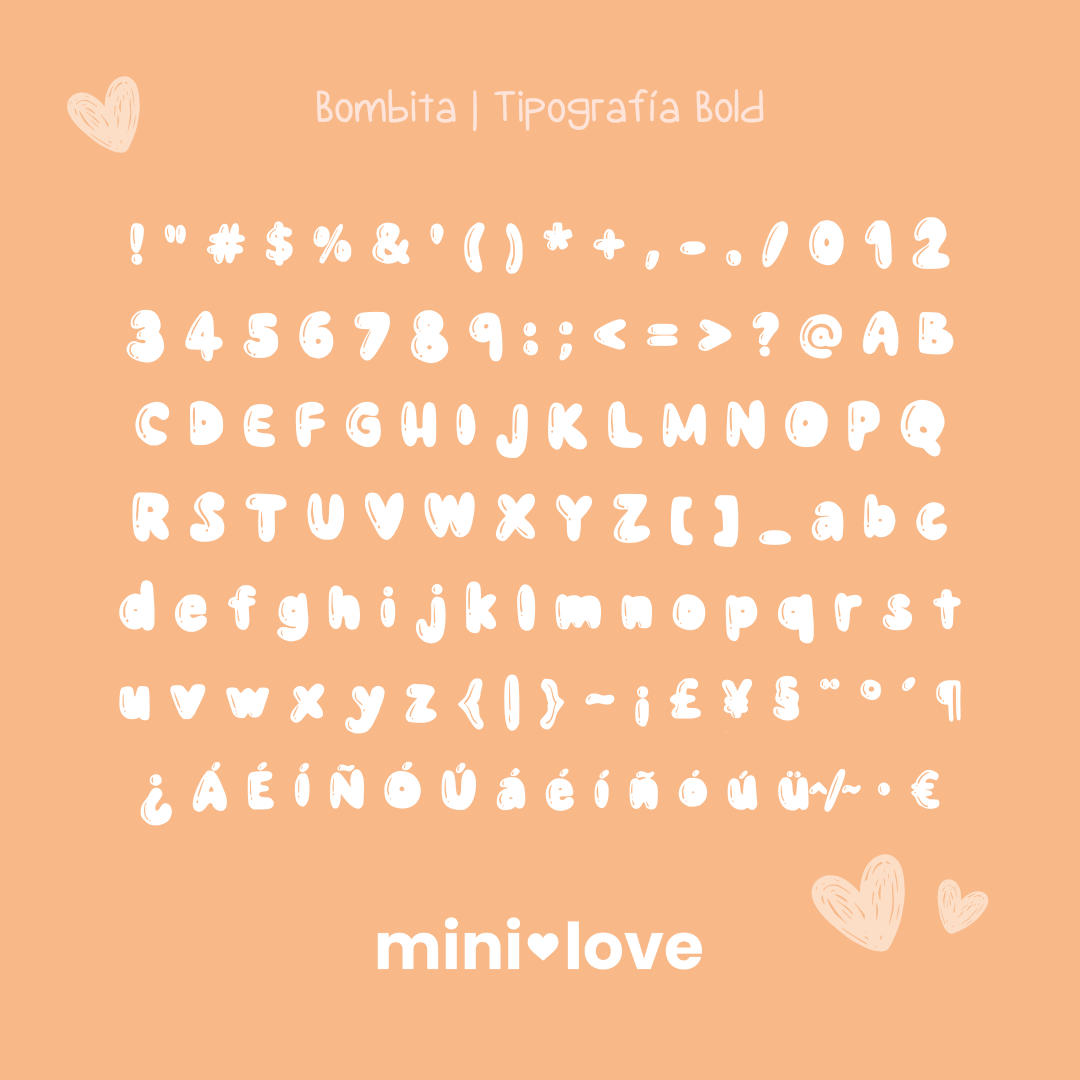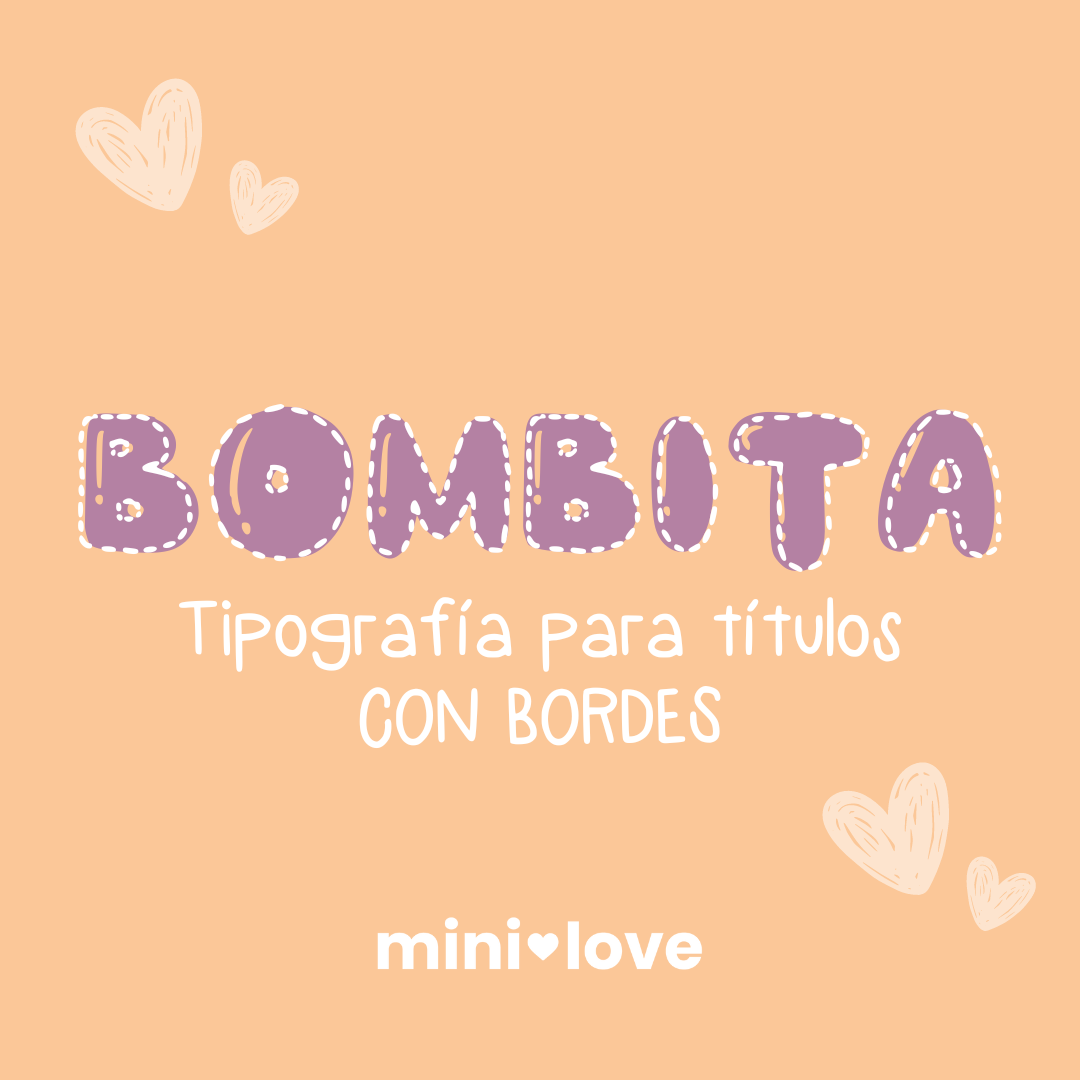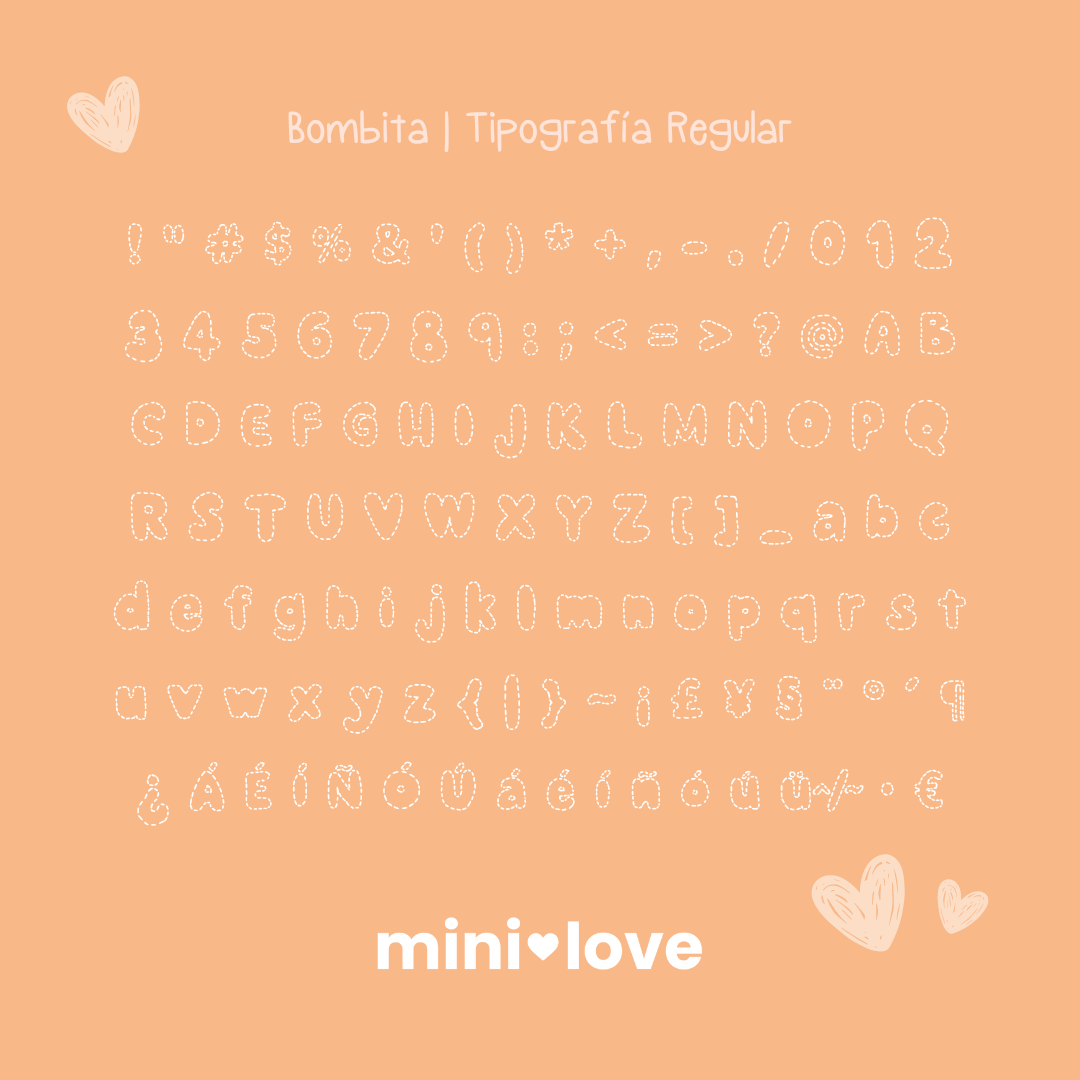
Tipografía Bombita
Esta tipografía estilo manuscrito en mayúsculas es la elección perfecta para darle un toque personal a los títulos de tu bullet journal, apuntes y anotaciones. Transforma tus escritos en una experiencia única, como si estuvieras escribiendo con tu propia caligrafía.
Esta tipografía tiene su versión Regular, con la que podrás ver la tipografía en línea y su versión Bold, donde podrás ver el relleno. Podrás personalizar tu tipografía al color que necesites.